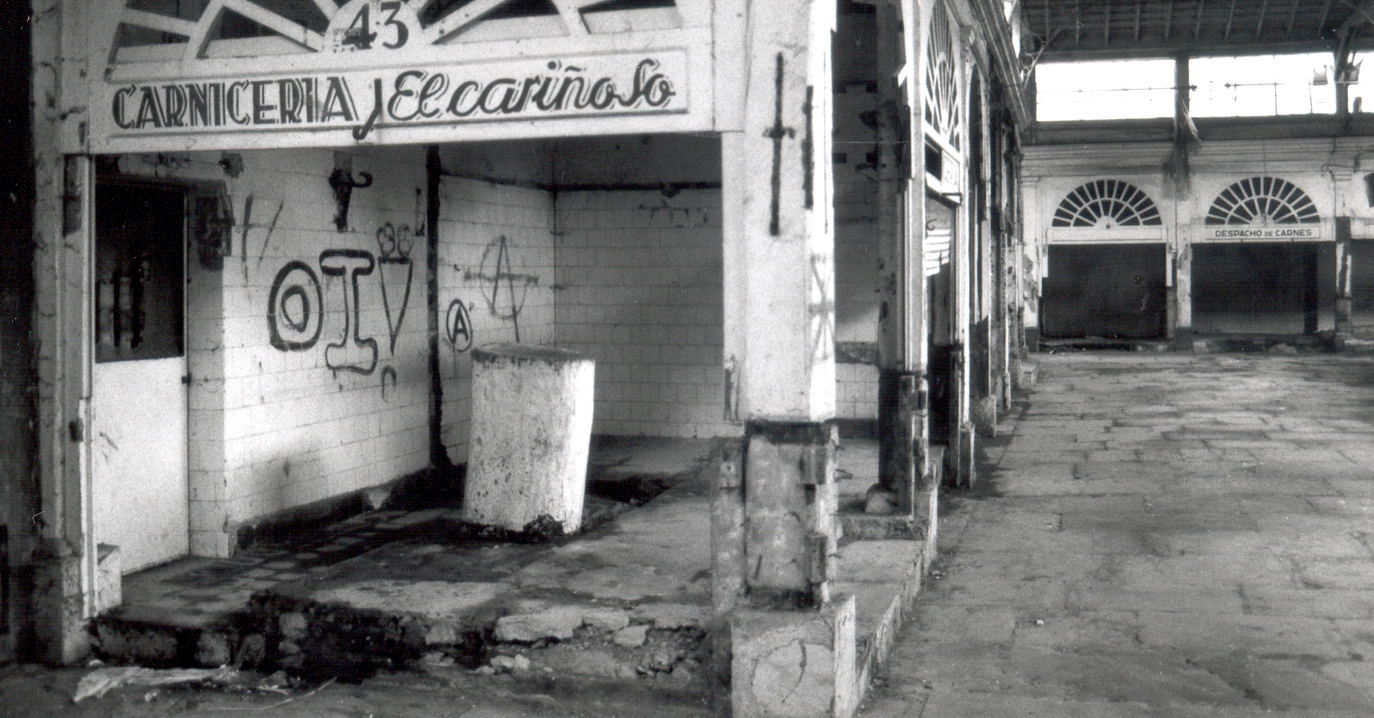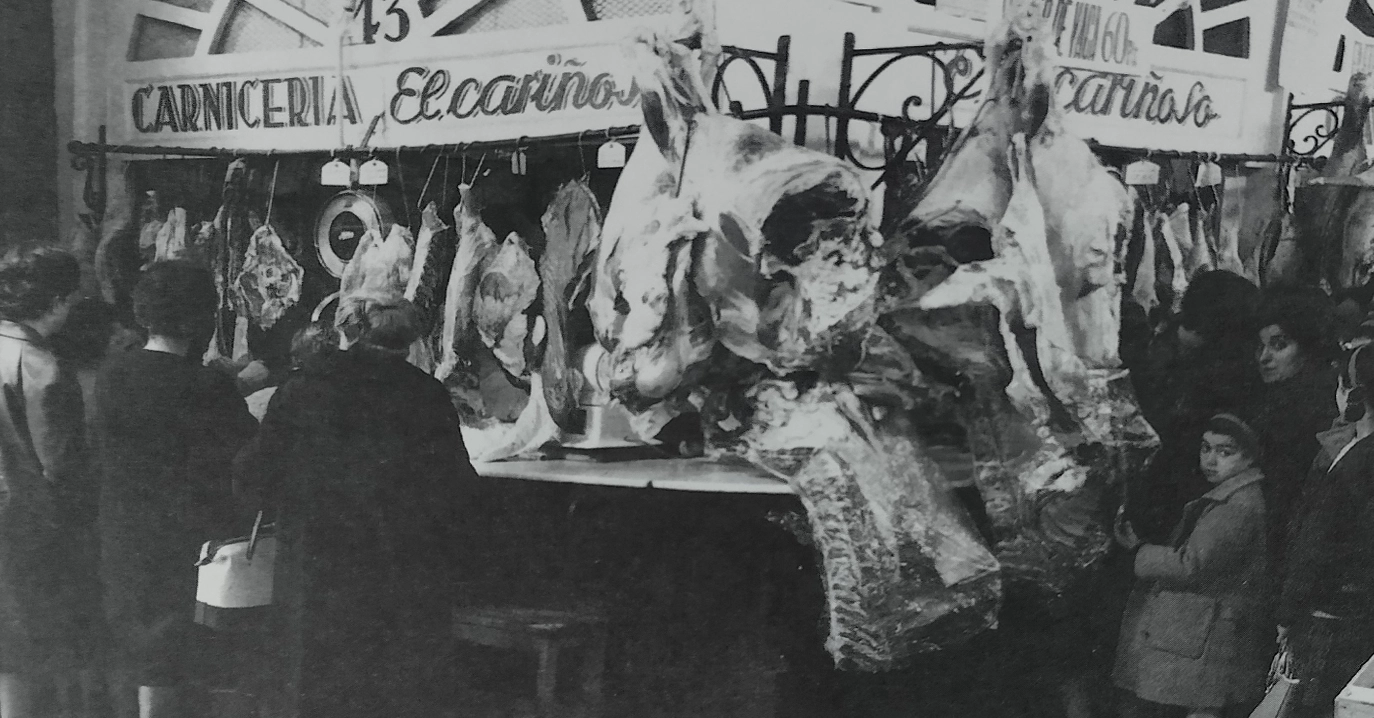
Carnicería El Cariñoso
El Mercado del Este, antes de su transformación, preservó parte de los puestos originales que hubo. Aparte, se podían ver todos los rótulos en distinta tipología, que van desde los pintados en madera hasta letras corpóreas en metal.
Este es uno de los casos, el de la «Carnicería Cariñoso» regentada por la familia Lavín Acebo (Liérganes). Como se ve en la fotos de archivo, aparte de su Tipografía, destacaba la puesta en escena.